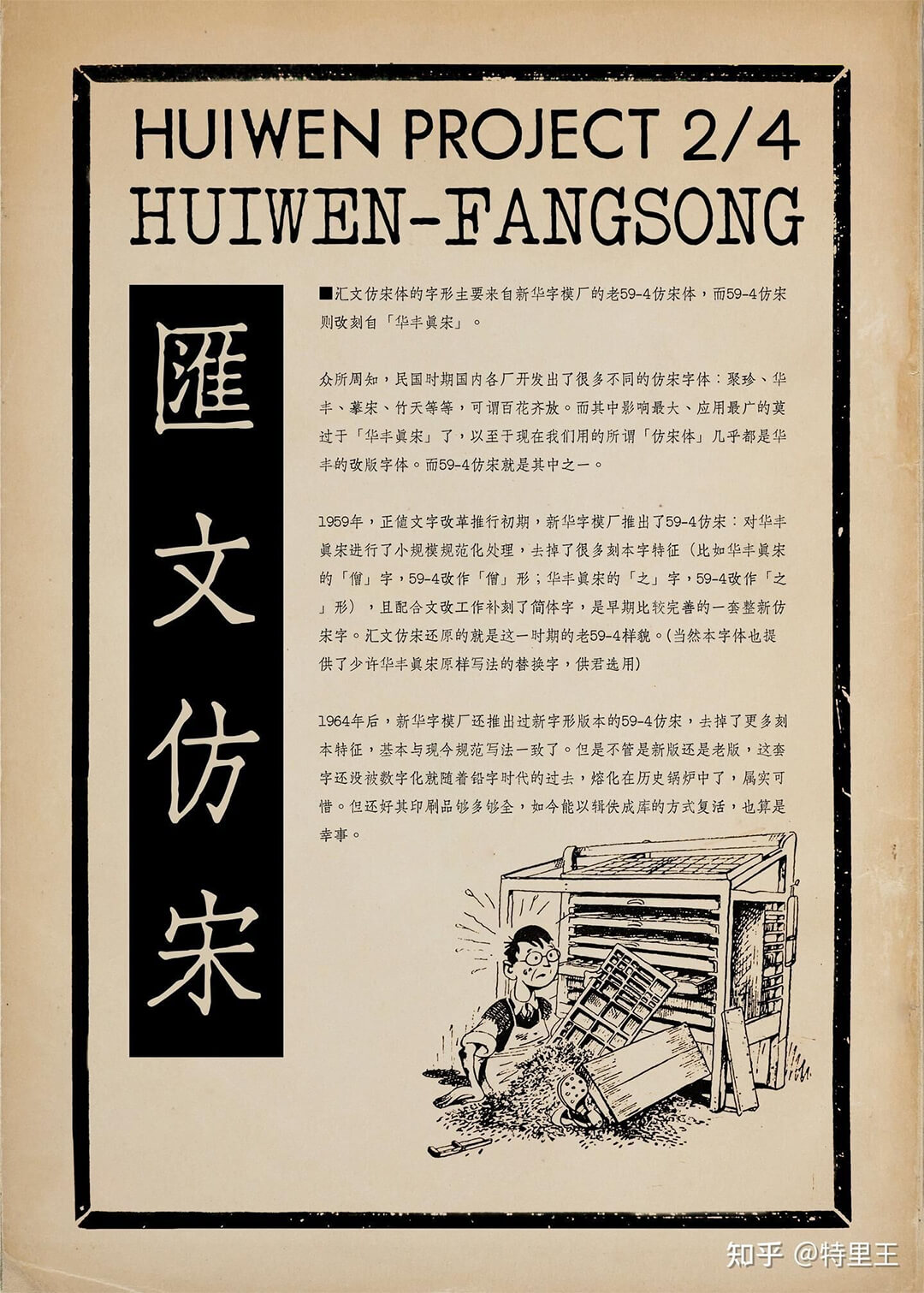
汇文仿宋体的字形主要来自新华字模厂的老59-4仿宋体,而59-4仿宋则改刻自「华丰眞宋」。
众所周知,民国时期国内各厂开发出了很多不同的仿宋字体:聚珍、华丰、摹宋、竹天等等,可谓百花齐放。而其中影响最大、应用最广的莫过于「华丰眞宋」了,以至于现在我们用的所谓「仿宋体」几乎都是华丰的改版字体。而59-4仿宋就是其中之一。
1959年,正值文字改革推行初期,新华字模厂推出了59-4仿:对华丰眞宋进行了小规模规范化处理,去掉了很多刻本字特征(比如华丰眞宋的「僧」字,59-4改作「僧」形;华丰眞宋的「之」字,59-4改作「之」形),且配合文改工作补刻了简体字,是早期比较完善的一套整新仿宋字。汇文仿宋还原的就是这一时期的老59-4样貌。(当然本字体也提供了少许华丰眞宋原样写法的替换字,供君选用)
1964年后,新华字模厂还推出过新字形版本的59-4仿宋,去掉了更多刻本特征,基本与现今规范写法一致了。但是不管是新版还是老版,这套字还没被数字化就随着铅字时代的过去,熔化在历史锅炉中了,属实可惜。但还好其印刷品够多够全,如今能以辑佚成库的方式复活,也算是幸事。